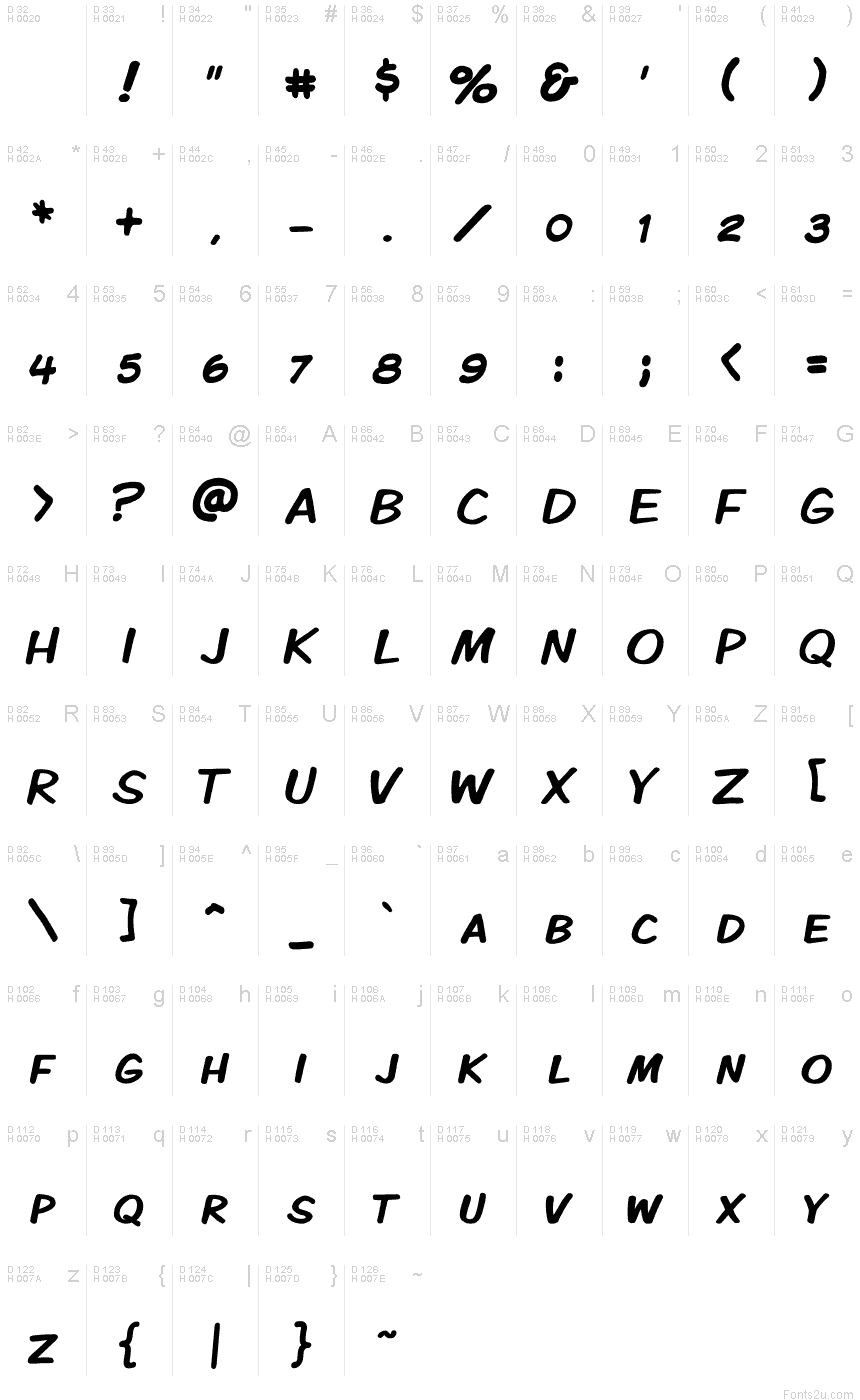
Komika Display Kaps od Wolfbainx & Apostrophic Labs to darmowy krój pisma w stylu komiksowym, pełen ekspresji i „tuszowego” charakteru. Jego masywne, wielkie litery pochylają się do przodu, zachowując luźny, ręczny rytm – jakby przed chwilą nakreślono je markerem na kartce. Grube kreski, zaokrąglone rogi i ciasne odstępy sprawiają, że każde słowo zyskuje wyrazistą, przebojową formę, która mimo swojej siły pozostaje przyjazna i „handmade”, unikając sztywnej elegancji.
Użyj Komika Display Kaps, aby nadać tytułom na okładkach komiksów, w sieciowych historiach obrazkowych, na plakatach dla dzieci, w menu gier, miniaturach na YouTube czy na wyrazistych naklejkach i badge’ach odpowiednią moc. Ten darmowy font najlepiej prezentuje się w dużym rozmiarze, niosąc efekty dźwiękowe, hasła czy krótkie nagłówki, które muszą wyskoczyć na pierwszy plan. W przypadku dłuższego tekstu połącz go z czystym bezszeryfowym krojem w mniejszym rozmiarze, aby Komika Display Kaps mogła pozostać w centrum uwagi, tam gdzie jej miejsce.
Komika Display Kaps